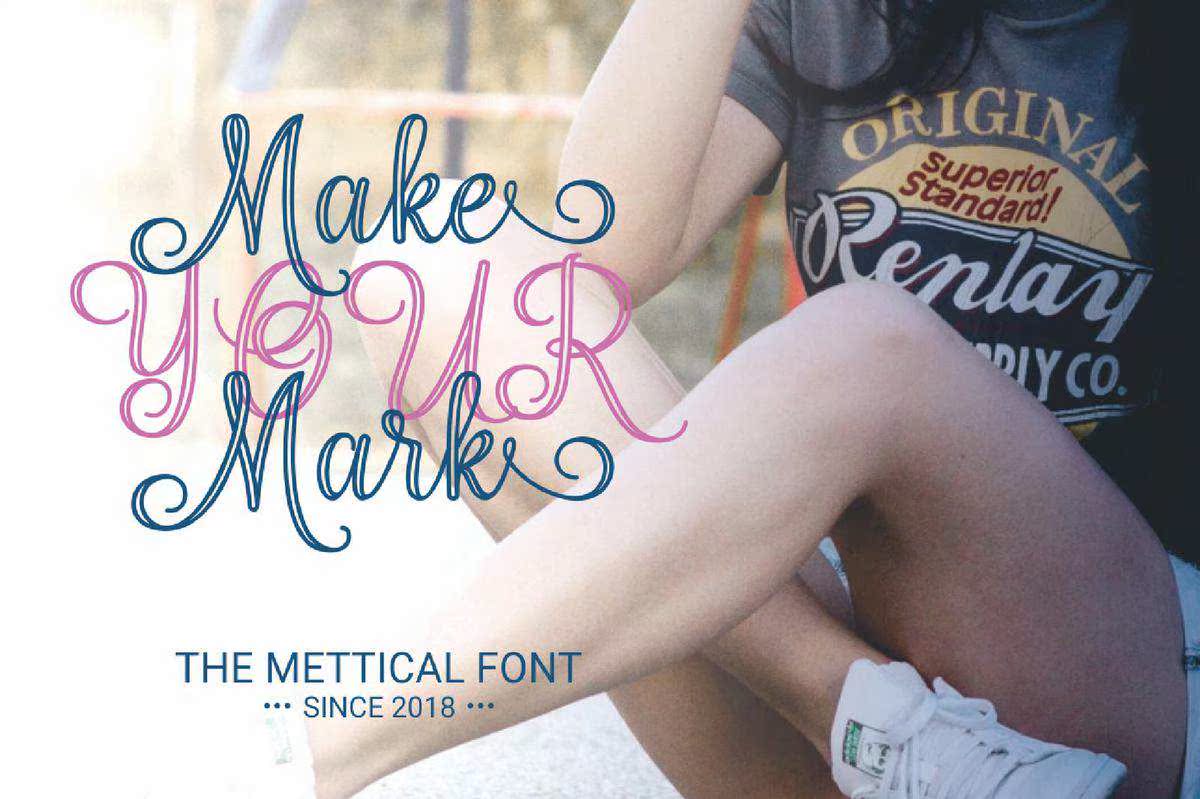
Metticalisabeautifulhandwrittenfont,具有独特的椭圆形风格;这是给你带来敏感和浪漫的最佳方式。它的特点是装饰性角色和舞蹈基线!。Metticalis Perfected适用于品牌项目、徽标、婚礼设计、社交媒体、广告、产品包装、产品设计、标签、摄影、水印、邀请函、文具以及任何需要使用智能字体的项目。Metticalis具有智能字体风格的智能字体;这是给你带来敏感和浪漫的最佳方式。它的特点是装饰性角色和舞蹈基线!。Metticalis完美适用于品牌项目、徽标、婚礼设计、社交媒体、广告、产品包装、产品设计、标签、摄影、水印、邀请函、文具以及任何需要精美手工品味的项目。